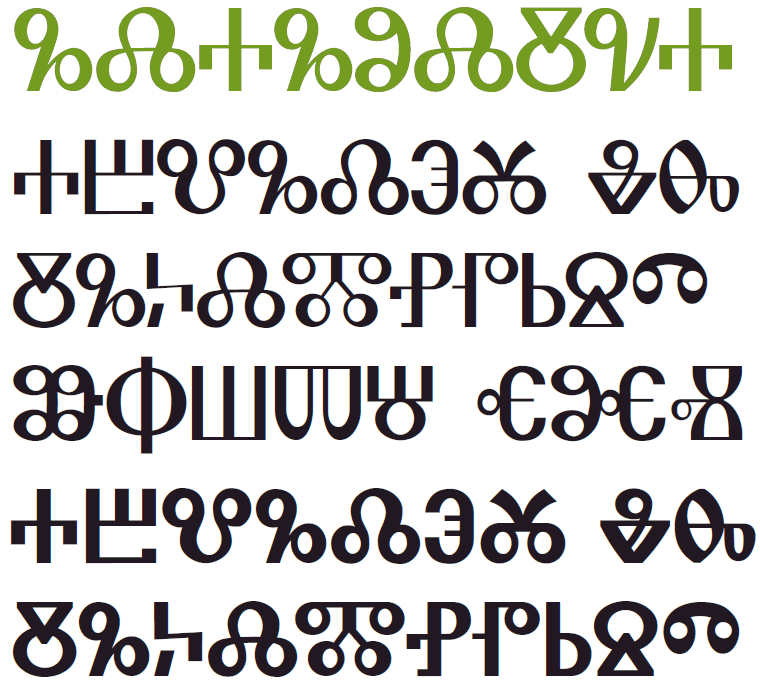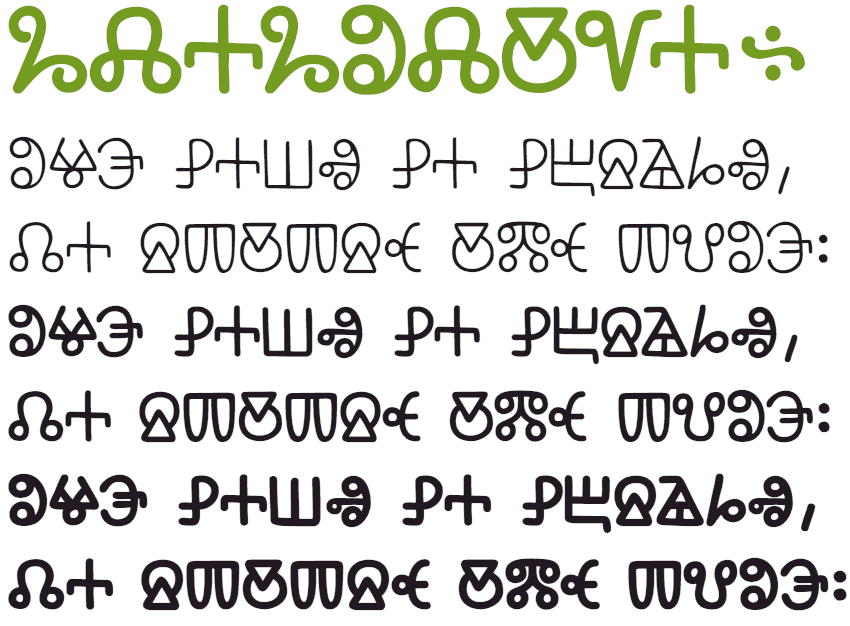
Glagolica Script EFN to zestaw 3 pięknych fontów.
Zestaw zawiera fonty w odmianach Cienkiej, Normalnej i Pogrubionej oraz PDF ze szczegółową tablicą znaków (posiadają różne spotykane warianty liter np. M, N, P, itd.).
Glagolica Round EFN to, przygotowana przez Fonty.PL, zestaw 2 czcionek z tradycyjnymi znakami Głagolicy Okrągłej w odmianach Normalnej i Pogrubionej.
Poszczególne litery (niektóre w kilku wersjach) zostały umieszczone w miarę możliwości fonetycznie i wszystkie są łatwo dostępne wprost z klawiatury. Zestaw zawiera tablicę znaków w PDF.